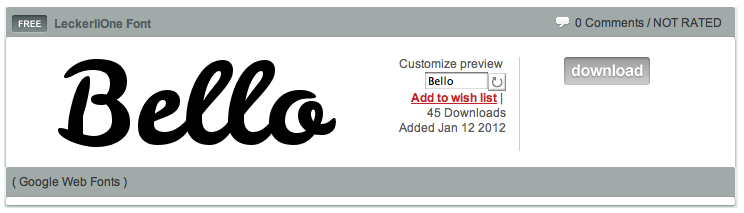
suche eine Schrift wie die Bello von Underware
ich will für eine Freundin eine Einladungskarte gestalten und hätte gerne eine Schrift wie die Bello von Underware...
Gibt es einen Freefont? Die creampuff habe ich schon probiert....
Gibt es noch andere?
Und wenn ich bei Freefobtanbietern suche...ist das handwriting? oder kalligrafie?
In welche Kategorie passt die denn?
Vielleicht so was?
Dazu ein paar Vorschläge der argentinischen Schriftenschmiede Sudtipos …
Das sind Freefonts? :neenee:
Oh, Du hast etwas gefunden.
Nee, beim Verlinken eben ist mir auch gerade aufgefallen, dass es Freefonts sein sollen. Habe meine Vorschläge deshalb wieder getilgt. Leider hattest Du es inzwischen schon beantwortet …
Ich denke, ich schau mal nach den GoogleFonts (google dein freund und helfer...)
Leckerli passt glaube ich ganz gut.
Nur noch dies: In welcher Kategorie müsste ich denn schauen, wenn ich bei dafonts z.b. so eine Schrift suche?
… Nur noch dies: In welcher Kategorie müsste ich denn schauen, wenn ich bei dafonts z.b. so eine Schrift suche? …
Ich würde bei "Brush" schauen.
Und auch beim Eichhörnchen hier und dort.
Das wird ja ganz unterschiedlich gehandhabt. Das könnte Brush, Calligraphy, Handdrawn /- written oder sogar Retro sein. Du kannst auch ein Bild deiner Schrift nehmen und bei whatfontis z.B. eingeben und dann Alternativen angezeigt (auch Freefonts).